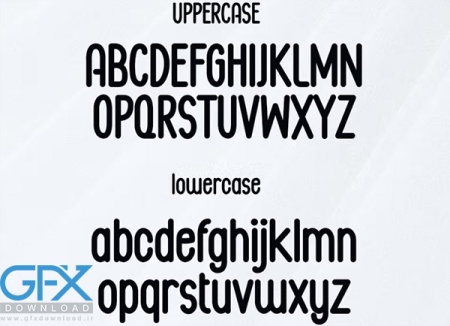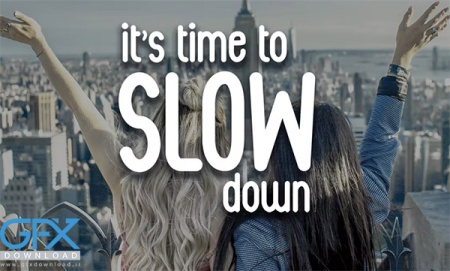
فونت انگلیسی Liquidy Zolla
دانلود فونت انگلیسی ساده Liquidy Zolla
در این پست با معرفی فونت زیبا Liquidy Zolla، که یک فونت معمولی و ساده است با شما همراه هستیم. فونت انگلیسی Liquidy Zolla حس منحصر به فرد و دوست داشتنی آن است. بسیار مناسب برای شما که به یک تایپ فیس برای طراحی لوگو، مجله، رسانه های اجتماعی، بروشور و بسیاری موارد دیگر نیاز دارید. شامل حروف بزرگ حروف کوچک - اعداد